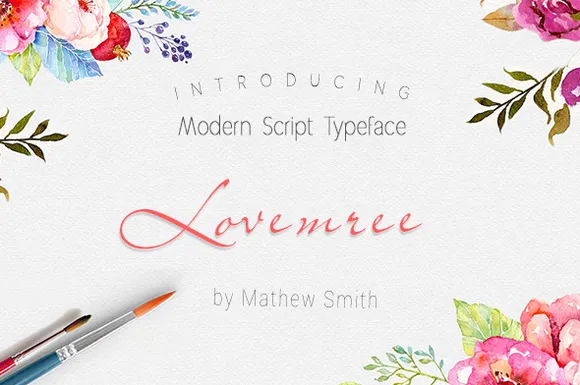
Lovemree Script Font – Download Grátis
Através de Lovemree Script Font você pode encontrar uma maneira criativa para assinar seus documentos ou criar identidade visual forte para sua marca. Com sua letra fluida e elegante, a fonte Camilla é perfeita tanto para criações de logotipos e identidades visuais quanto para designs de moda ou mesmo como base para frases escritas à mão. Suavemente fluida, esta fonte permite que você personalize completamente o estilo do seu documento, tornando-o único e memorável. Com a Lovemree Script Font, é fácil criar um design atraente e sofisticado que se destaca em qualquer cenário.